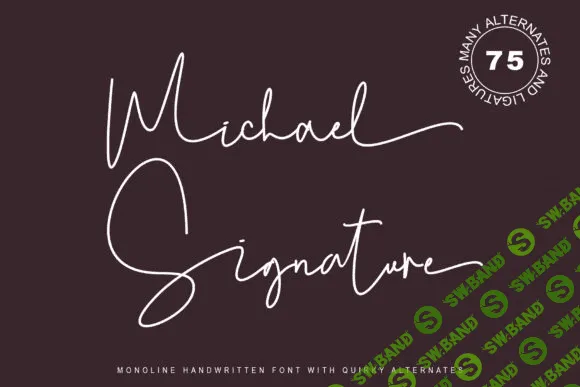
Название: Michael Signature Font
[Creativefabrica] Michael Signature Font
Майкл Подпись - тонкий и скорописный рукописный шрифт.
Он выглядит красиво на различных дизайнах, требующих персонализированного стиля, таких как свадебные приглашения, благодарственные открытки, свадьбы, поздравительные открытки, логотипы и так далее. Этот шрифт закодирован PUA, что означает, что вы можете получить доступ ко всем глифам и следам с легкостью!